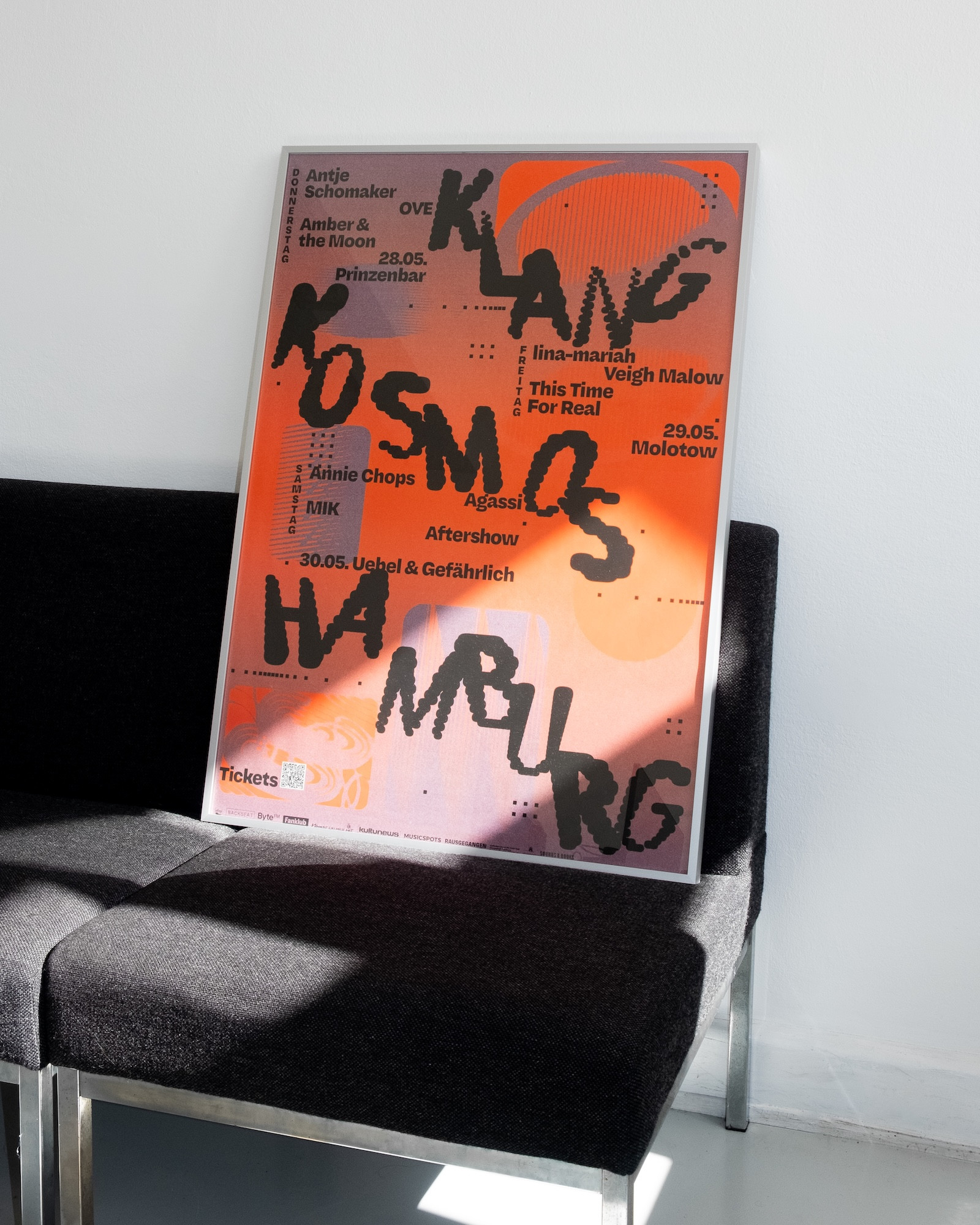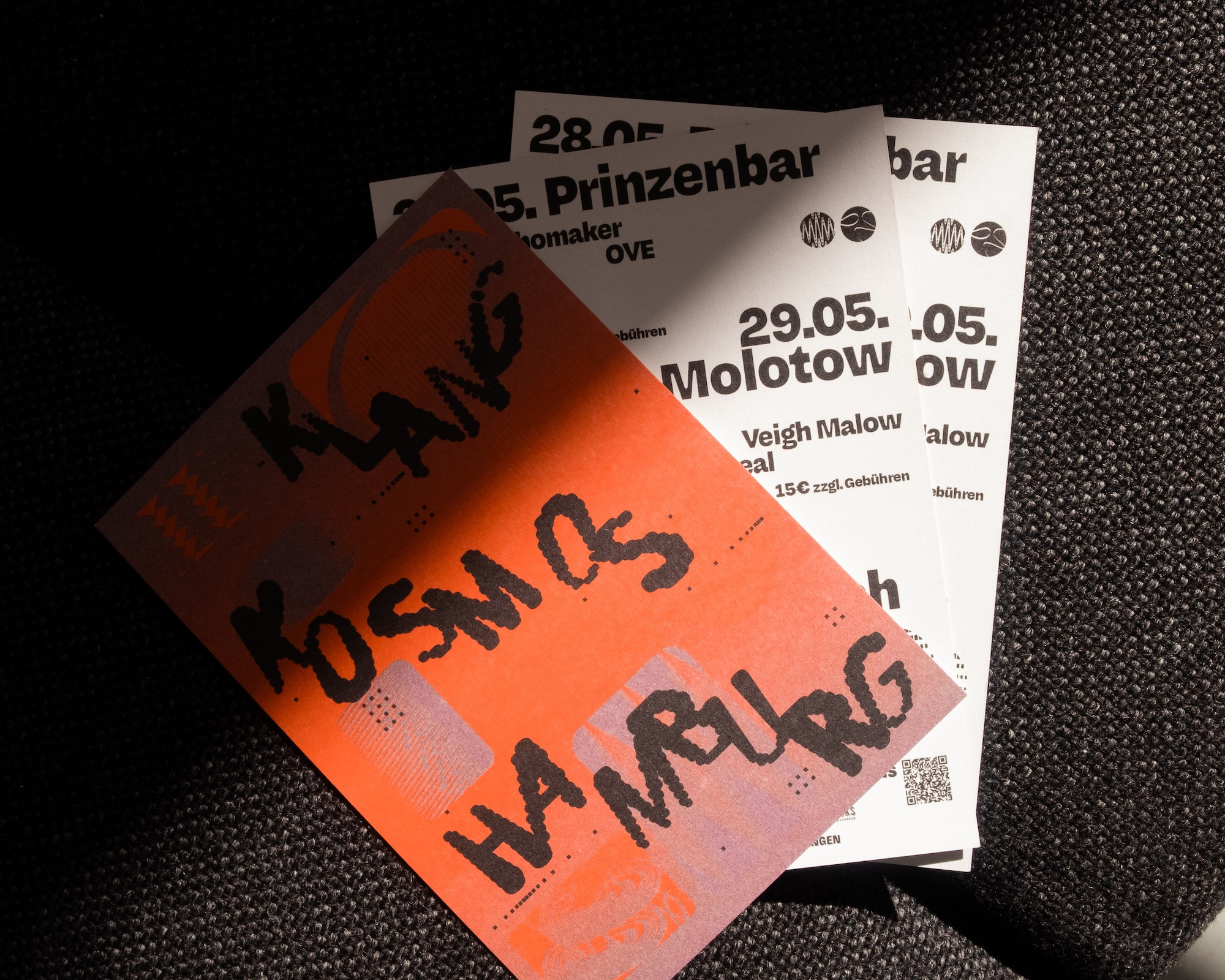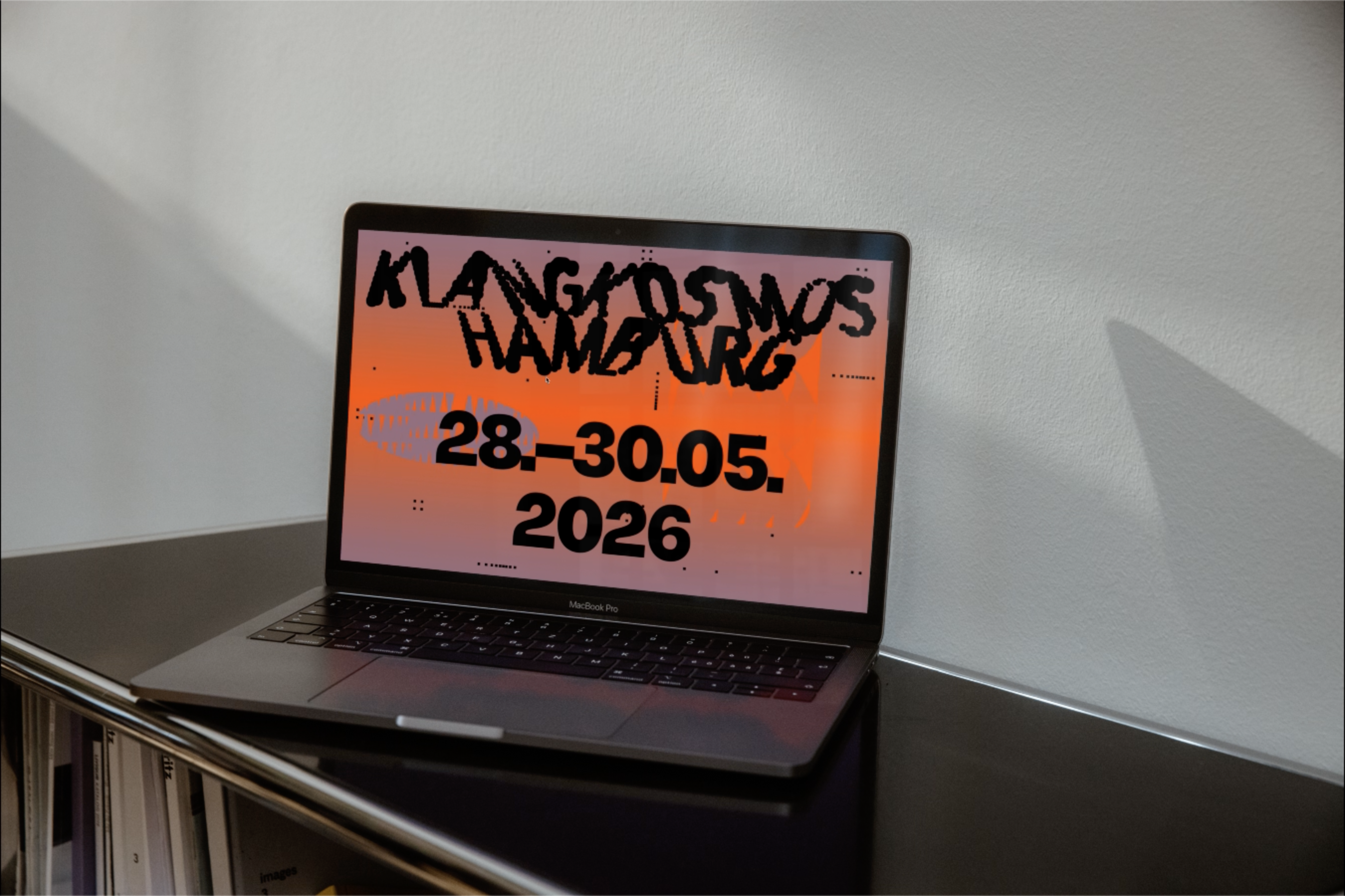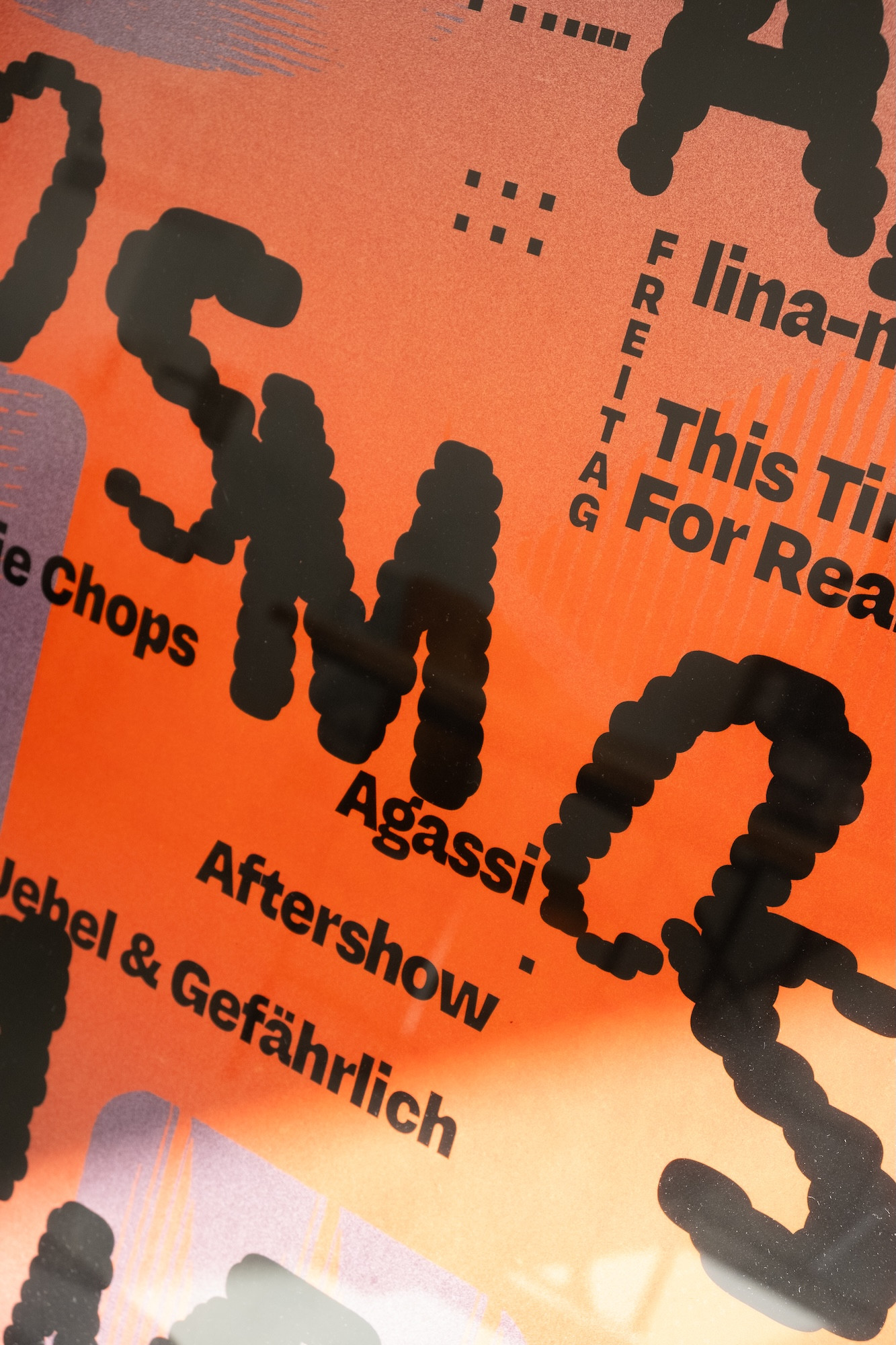
Klangkosmos, das Club-Festival für Bands aus Hamburg geht in die zweite Runde.
Jeweils drei Acts treten an drei moderierten Abenden in drei Hamburger Clubs auf. Seit der Hamburger Schule ist viel Wasser die Elbe hinabgeflossen. Aber wie klingt Hamburg heute? Der Klangkosmos Hamburg will die lokale Szene stärken, sie sichtbar machen, vernetzen und feiern. Organisiert wird das Ganze von Sebastian Król (Backseat / Fanklub / Norden Festival / Karwendel) und Wiebke Kruse aka Betti Kruse.
Im Zentrum der visuellen Identität steht das Logo, entwickelt auf Basis der variablen Schrift Harber von Benoît Bodhuin. Durch die zahlreichen Gestaltungsachsen der Schrift entsteht ein spielerisches, facettenreiches Logo, dessen Buchstaben sich individuell durch feine Punktstrukturen unterscheiden. So vermittelt das Logo eine lebendige, klangvolle Dynamik.
Grafische Elemente, die an die physische Sichtbarmachung von Schallwellen erinnern, ergänzen das Erscheinungsbild und unterstreichen das Thema Klang. Das Farbspektrum reicht in diesem Jahr von einem intensiven Orange hin zu einem satten, warmen Violett. Ein Rauschfilter verleiht den Farben zusätzliche Tiefe und Vielschichtigkeit. Die begleitende Typografie — gesetzt in der Gantry von Oh No Type Co. — ergänzt die Gestaltung mit ihrer weichen, einladenden Anmutung. Ihre vielfältigen Formen spiegeln die klangliche Vielfalt des Festivals wider.
Die CI wurde entsprechend der neuen Farben angepasst und auf die folgende Medien angewendet: Logo, Plakat, Website, Flyer, Werbemittel (Stoffbeutel, Klebetattoos) & digitale Anwendungen für Social Media und Onlinemedien.
Schrift: Harber von Benoît Bodhuin
& Gantry von OH no Type